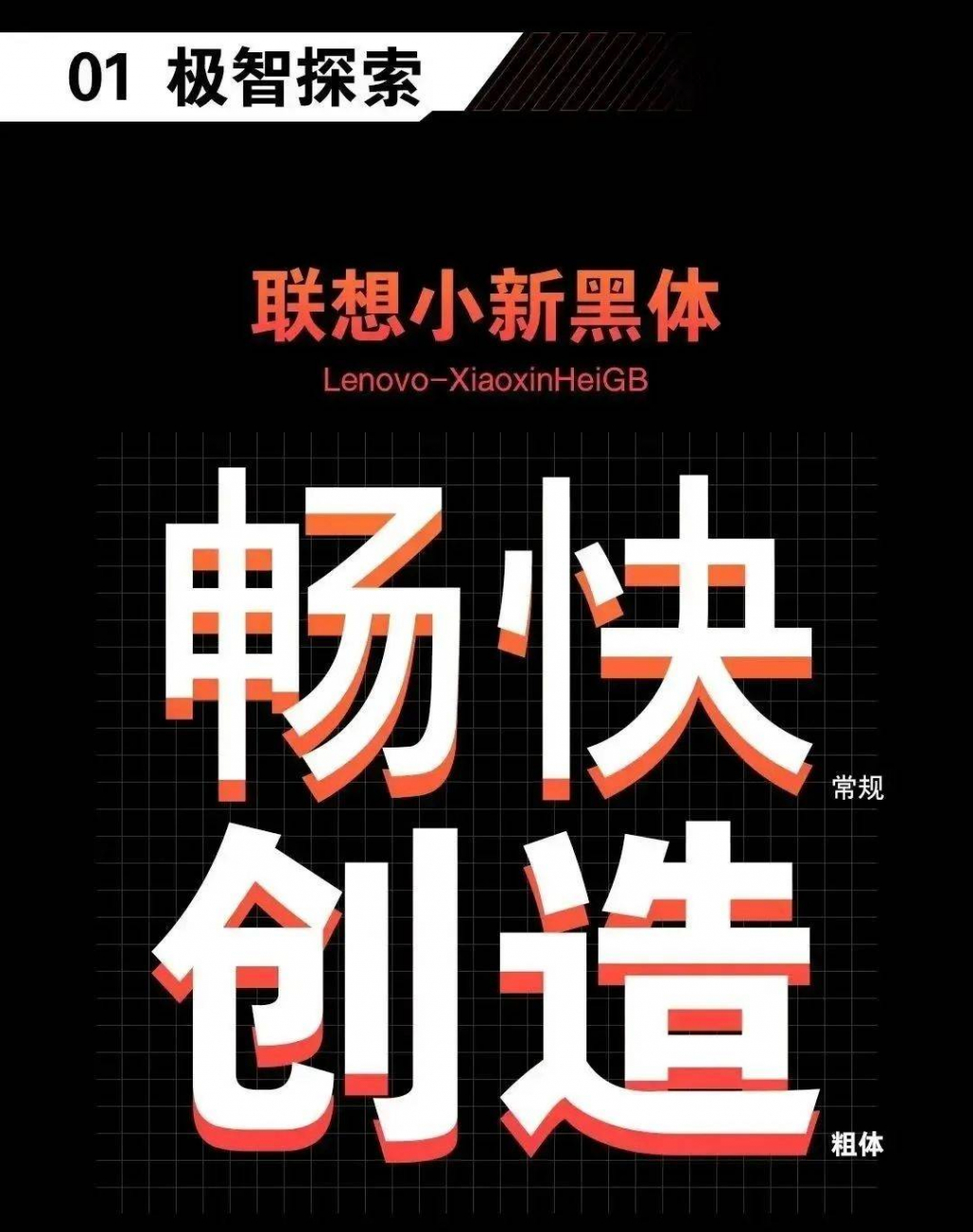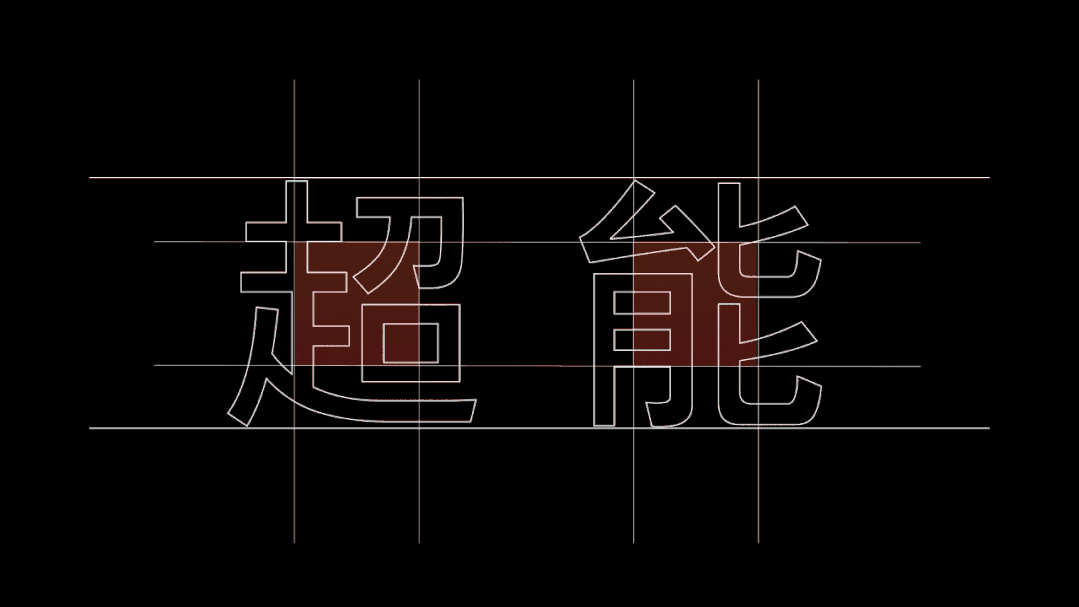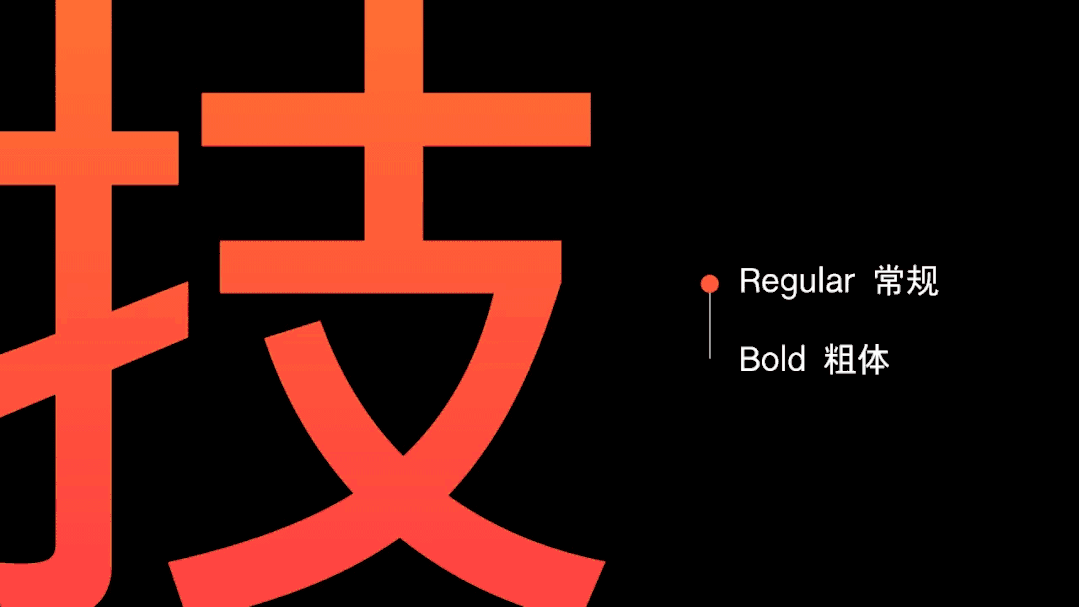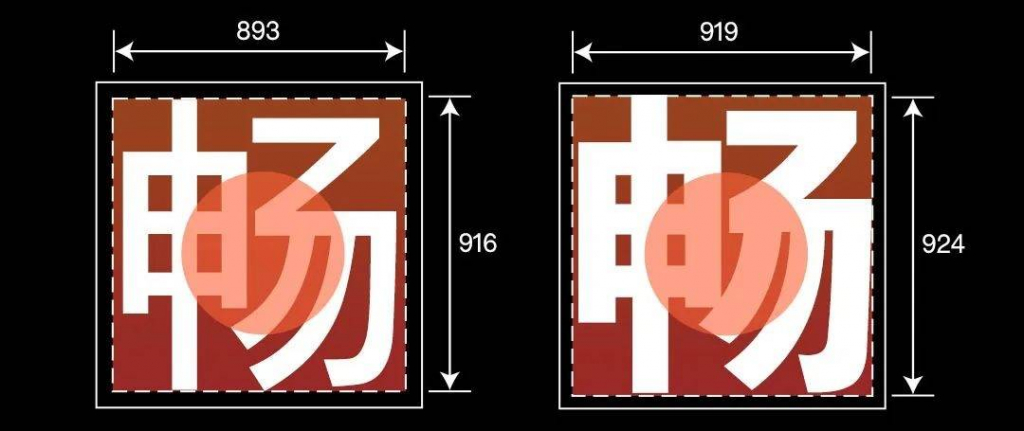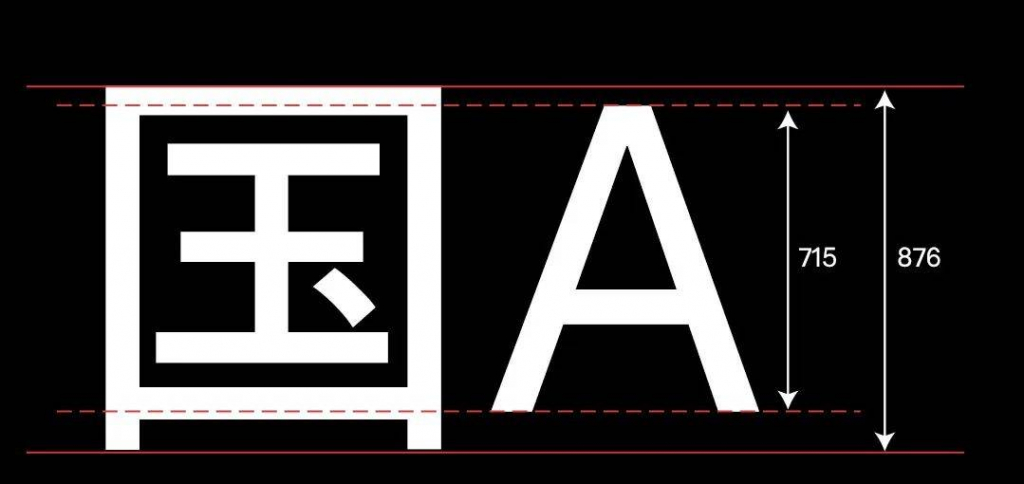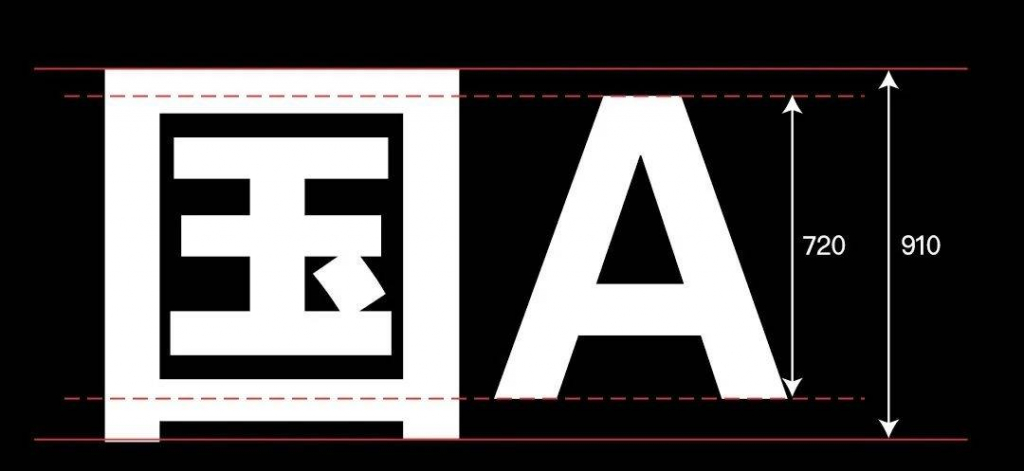
“人”字头等偏旁部首采用更具手写感的笔触,在中性的科技感中融合人文气息,创造出科技与人文的平衡,成就更好的视觉体验。
“口”字部首采用偏传统的出头造型,更符合用户的阅读习惯,优化辨识度与体验感。
为深度匹配品牌需求,联想小新黑体提供常规、粗体2款字重,同时在6763汉字基础上,增加400个常用汉字,可满足正文、说明文、标题等多种场景的应用需求。
联想小新黑体常规体
字面框与字身框占比82%左右,大段排版时增加阅读舒适性。相对缩小的字宫,带来更多的视觉关注力。
联想小新黑体粗体
字面框与字身框占比85%左右,重点信息、标题使用时醒目易读;相对稍微内收的字宫,提升了人文感。
笔画尾端设计兼顾传统字体的法度和意态,撇捺笔画的弧线流畅,末端收笔平缓柔和。
撇捺等弧线笔画采用了上端略微上扬、下端略微平直的线条,赋予字体灵动感,笔画两端采用接近垂直外侧切线的角度处理,既没有锐角端面的犀利感,又没有纯垂直端面的冰冷感,整体营造出舒适柔和的人文美感。
西文的笔画末端统一采用平切的手法,笔画转折处呈现自然流畅的弧线,整体简洁又不失优雅,呈现清爽利落的秩序感与精简的视觉效果。